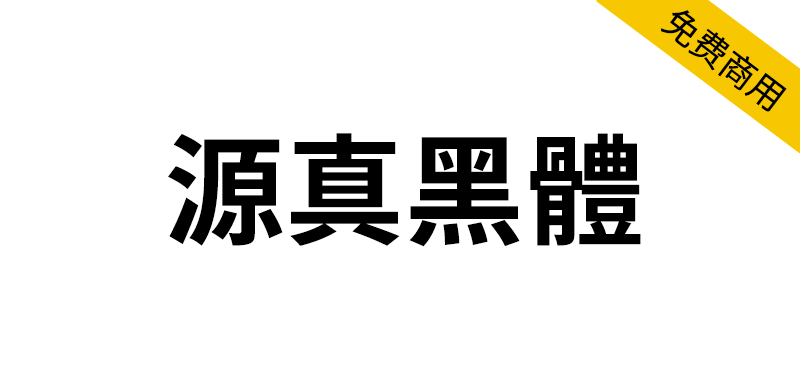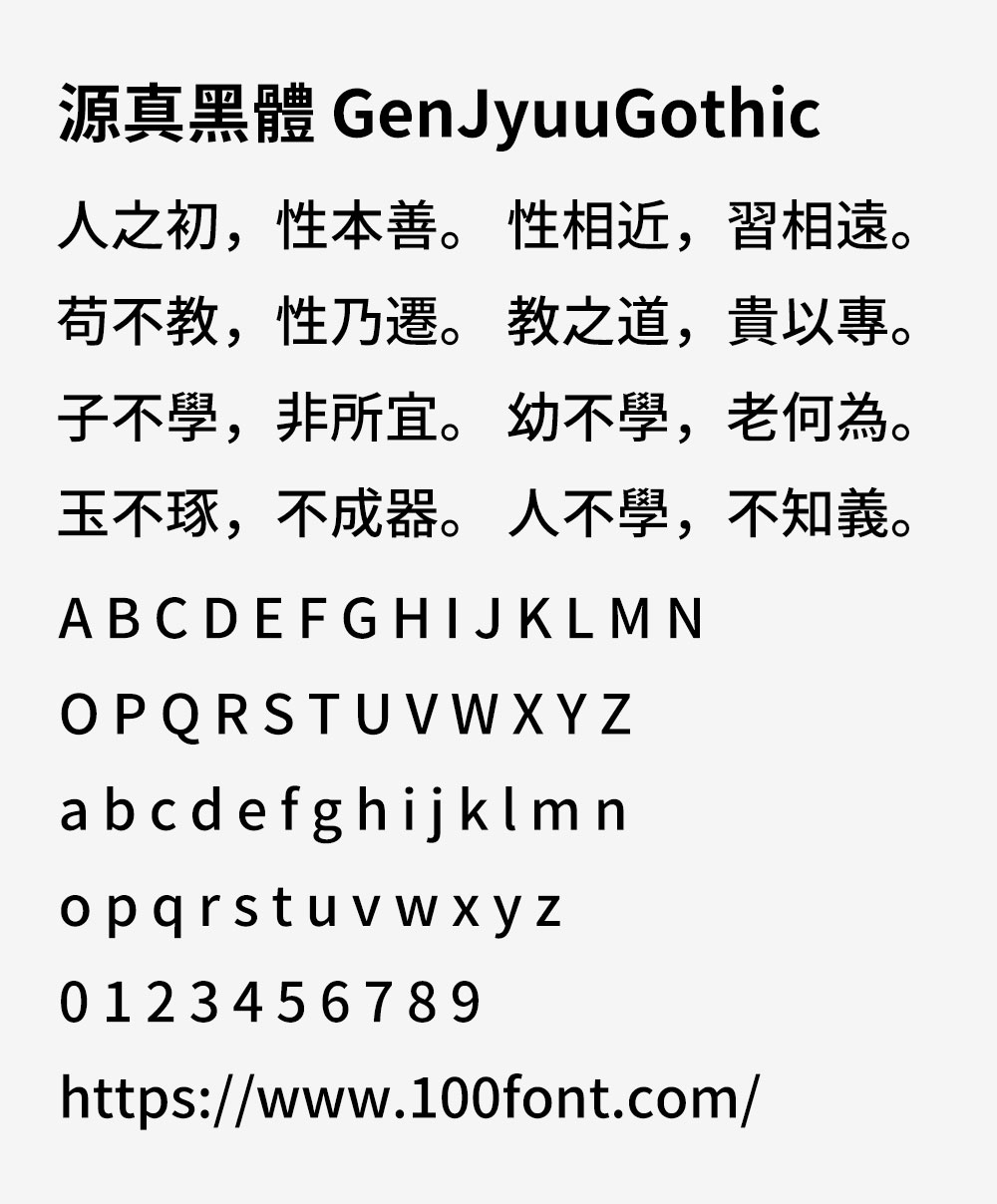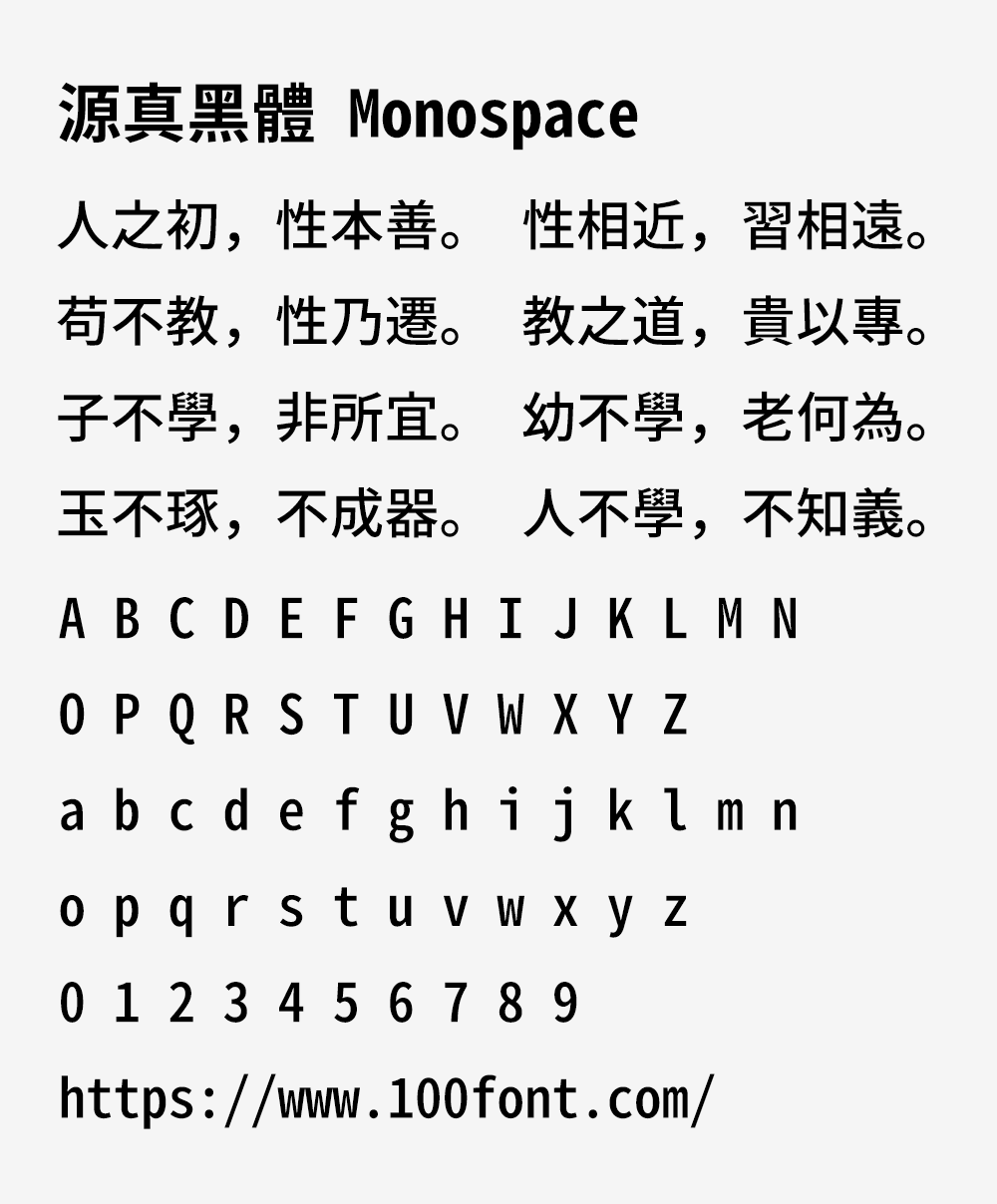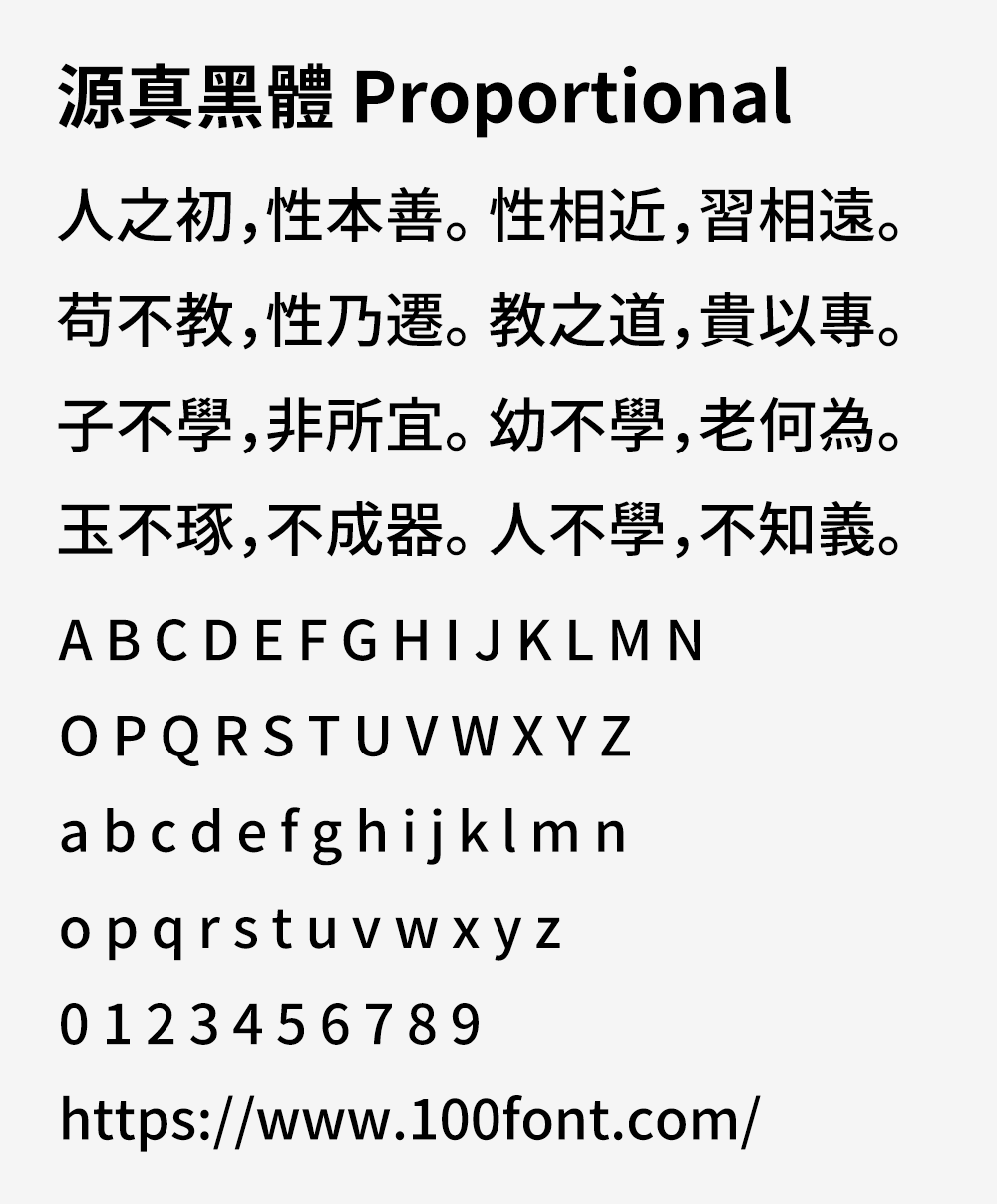
源真黑体(源真ゴシック)是基于开源字体“思源黑体”修改衍生而来,支持繁体中文以及日文,保留了思源黑体原版的优雅以及高可读性的特色,也是提供了 7 种不同的字重、3种字形样式 (包括等宽字体、比例字体)。格式上转换成 TrueType (TTF) 版,细节上也做了很多的调整与变化,使得整套字体看起来更加锐利清晰,更适用于大量文字阅读显示、代码编程、排版、打印等。
源真黑体的字重共有“一般、标准、中黑、细体、特细体、粗体、特黑体”7种。另外还有等宽字体 Monospace (适合用于编程写代码)、Proportional 比例字体 (字符宽度不同),细节上看起来更加锐利清晰,更适用于大量文字阅读显示、代码编程、排版、打印等。